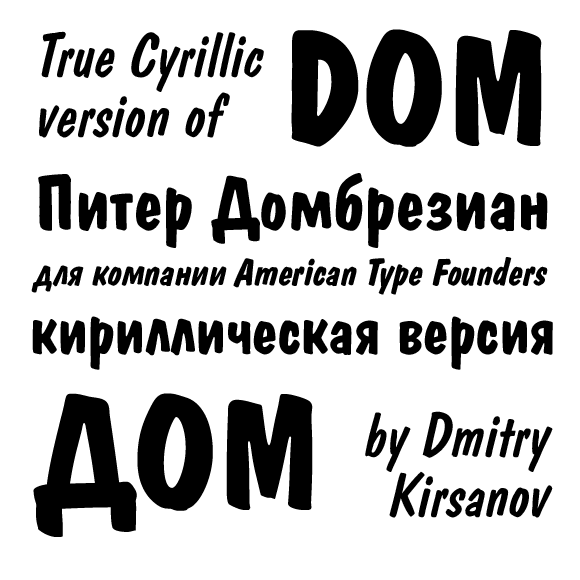
Шрифты для комиксов и мультяшные шрифты
Хочу представить вашему вниманию небольшую подборку, в которую вошли шрифты для комиксов, а так же мультяшные шрифты. Выбрал наиболее интересные и редкие, на мой взгляд. И еще все они поддерживают кириллицу, такие трудно найти.
1. Один из классических шрифтов, которые используют в комиксах. В нем только прописные буквы, легкие небрежность, и наклон, и разная толщина линий. В общем в баллонах чьих-то комиксов вы его наверняка встречали, попробуйте вставить в свои.
2. Если переводить название этого шрифта, получится что-то типа “куриная задница”. Я не знаю почему так. Мне этот шрифт приглянулся необычной формой и полосатостью. Думаю вполне уместен в каких-то мультипликационных заголовках и всяком таком. Имеет как прописные, так и строчные символы.
3. Брутально угловатый, резкий, жирный шрифт. Тоже видал где-то в комиксах.
4. Этот мне напоминает шрифт из старых мультиков, типа “Ну, погоди!”. Ну там когда авторов перечисляют в титрах. Похож очень по-моему. В общем для стенгазет, новых годов и прочих подобных детских тем. Подойдет идеально.
5. Еще один типичный шрифт из комиксов. Во всевозможных человеках пауках, росомахах, марвелах и прочих супергероях вы его обязательно встретите. Строчных традиционно нет.
6. Сказочно – эксцентричный, так бы я его назвал. Очень понравился этот шрифт. Асимметрия его не мешает чтению, но втыкает большую изюмину в его мякоть. Прекрасно подойдет для оформления каких-нибудь волшебных сказок или заклинаний. Ну или еще для чего-то.
7. Утонченный, резковатый, слегка разнузданный. Не знаю где я его видел , то ли в комиксах, то ли в мультиках?
8. Каменно – треснутый шрифт. Подойдет, естественно, для легенд о каменных чуваках.
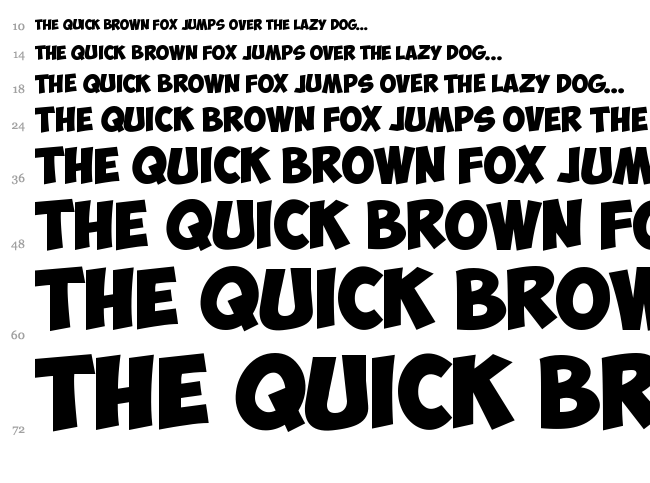
В классических комиксах шрифт обычно рисованный. Более того, в американских мейджорских издательствах комиксов рисованем шрифта в диалогах (это называется «леттеринг») занимается отдельный человек (хотя звукоподражательные слова может рисовать и сам художник.)
Существуют определенные стандарты на рисунок такого шрифта: как правило, это рубленый шрифт (шрифт без засечек), только прописные буквы, уменьшенный интерлиньяж (межстрочное расстояние), широко употребляется выделение отдельных слов полужирным и наклонным начертанием.